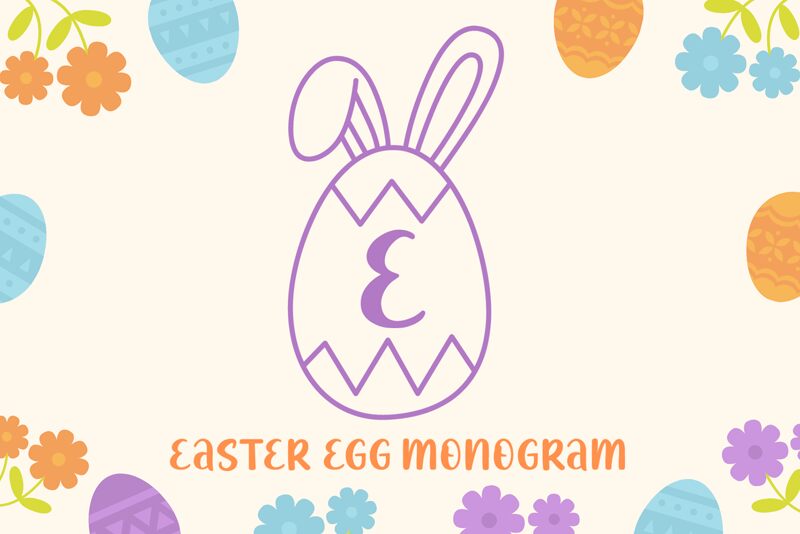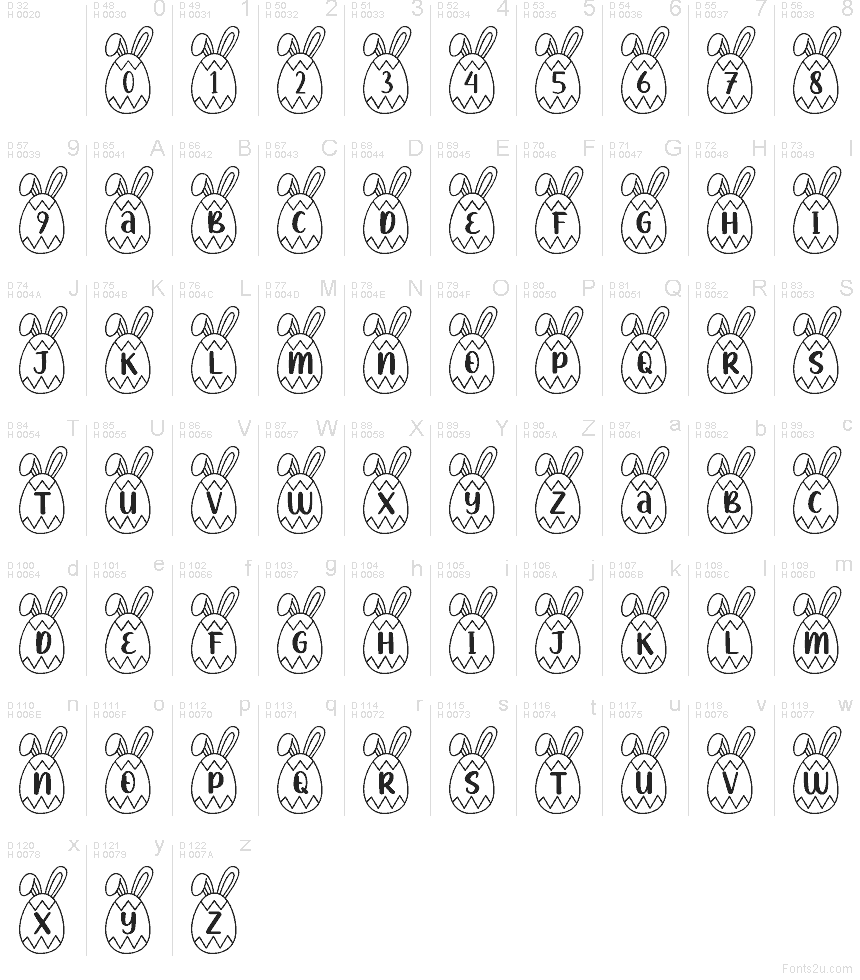
Easter Egg Monogram
A fonte Easter Egg Monogram da AEN Creative Studio é uma tipografia gratuita com temática de Páscoa, composta por molduras em formato de ovo, bordas em ziguezague e orelhas de coelho no topo. As letras encaixam-se no centro de cada ornamento, conferindo ao conjunto um estilo de contorno simples, desenhado à mão, perfeito para projetos de primavera e iniciais personalizadas.
Easter Egg Monogram funciona muito bem em cartões de identificação festivos, etiquetas para cestas, rótulos escolares, lembrancinhas de festas, páginas de scrapbook e convites sazonais. Esta fonte gratuita também se adapta a logotipos decorativos, detalhes em embrulhos de presente e elementos de banners quando você deseja um motivo de Páscoa claro com espaço para uma única letra ou inicial.